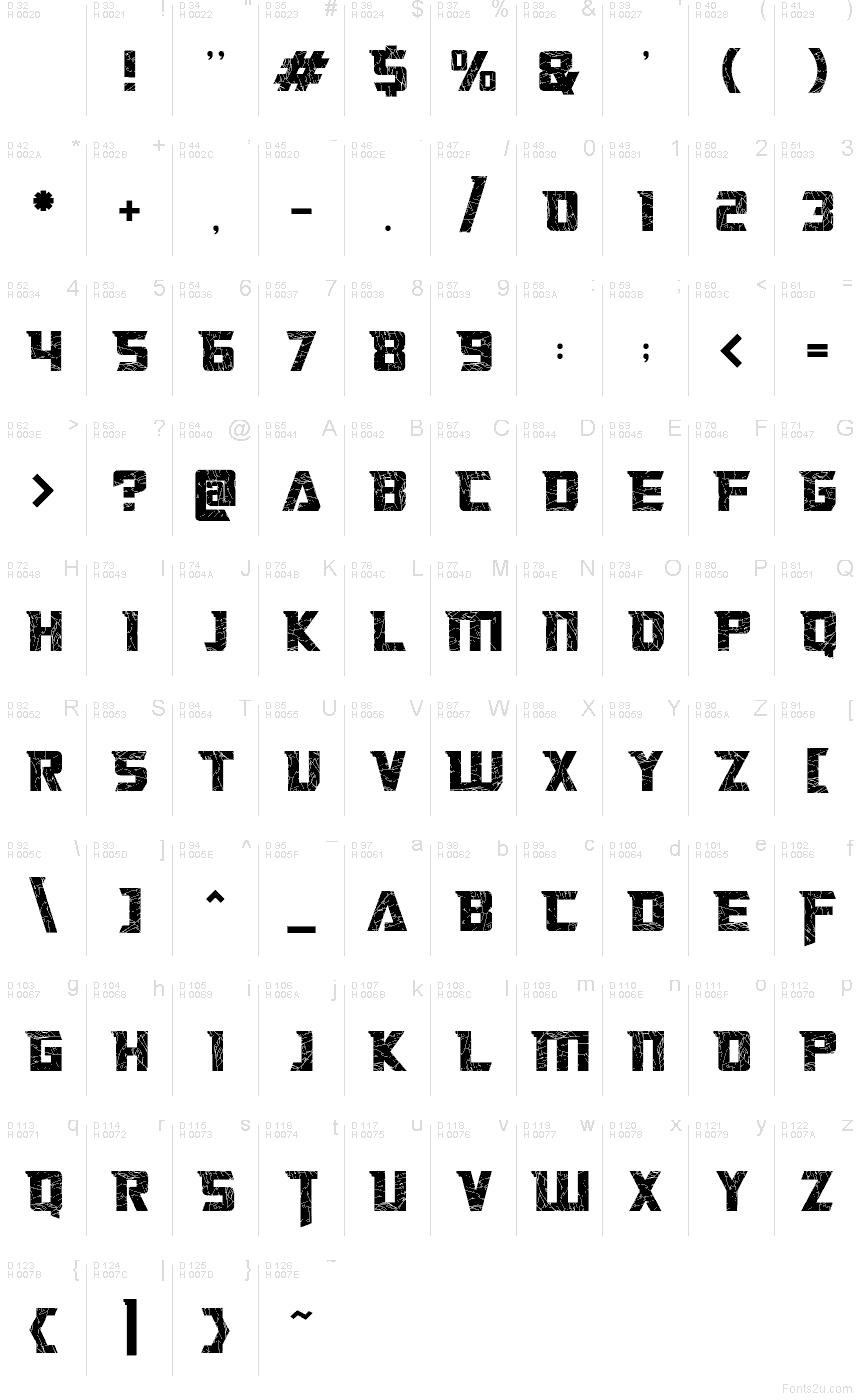
Turbo Type Four od Putracetol Studio je bezplatné techno display písmo definované hustou, popraskanou texturou, která prochází každým písmenem jako prasklý pancíř. Toto opakující se zpracování povrchu dodává designu drsnou, poškozenou estetiku, díky níž blokové tvary nepůsobí dojmem vyleštěného stroje, ale spíše jako něco namáhaného, rozštípnutého nebo poznamenaného bojem.
To z něj dělá přirozenou volbu pro názvy her, sci-fi plakáty, branding e-sportů, obaly alb a grafiku akcí, kde musí nápisy vyvolat napětí dříve, než se objeví jakékoli jiné vizuální prvky. Písmo nejlépe vynikne u krátkých nadpisů a log, protože roztříštěný vnitřní vzor dodává i jednoduchým slovům silnou grafickou roli.
Turbo Type Four